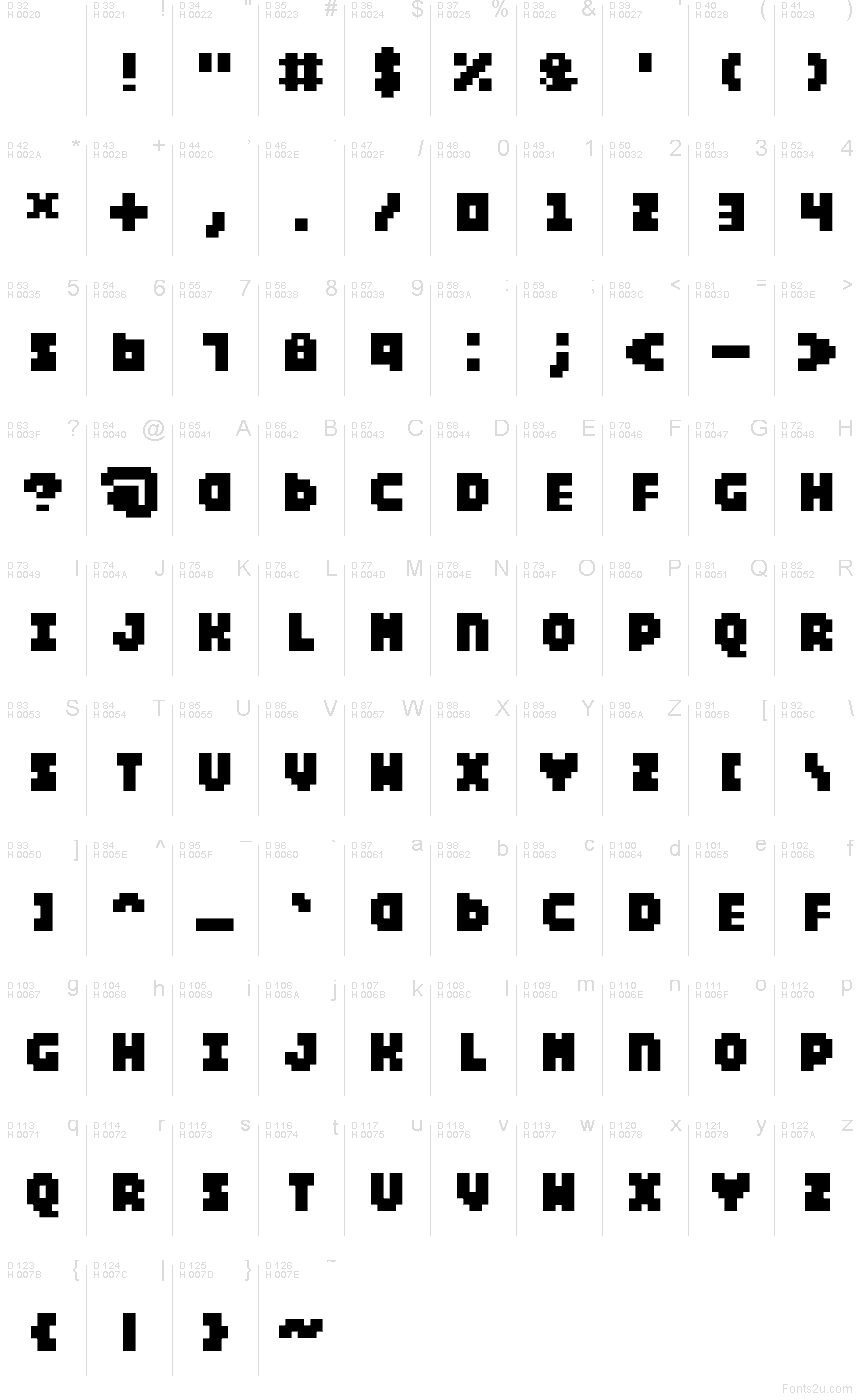
PixelNarrator Písmo
Pixel Narrator od Pixilized je bezplatné pixelové titulkové písmo skládající se z masivních bloků zarovnaných na mřížku. Jeho čtvercové řezy a odstupňované okraje připomínají neotesané tvary nápisů z raných arkádových her. Tvary jsou široké a nezaměnitelně digitální.
Pixel art, dlaždicová pozadí a ikony v nízkém rozlišení sdílejí stejnou ostrohrannou geometrii, díky čemuž je písmo přirozenou součástí herní grafiky a plakátů na arkádové akce. Může také propůjčit technologickému merchandisu a grafice streamovacích kanálů přímý vzhled připomínající obrazovku namísto hladkého moderního vzhledu. Pro nezávislé herní studio nebo značku retro elektroniky se písmo může stát kompaktním systémem loga, který odráží pixely použité napříč produkty a propagačními materiály.
Udělal jsem to pro svou hru. Jmenuje se Narrator, protože je pro vypravěče.